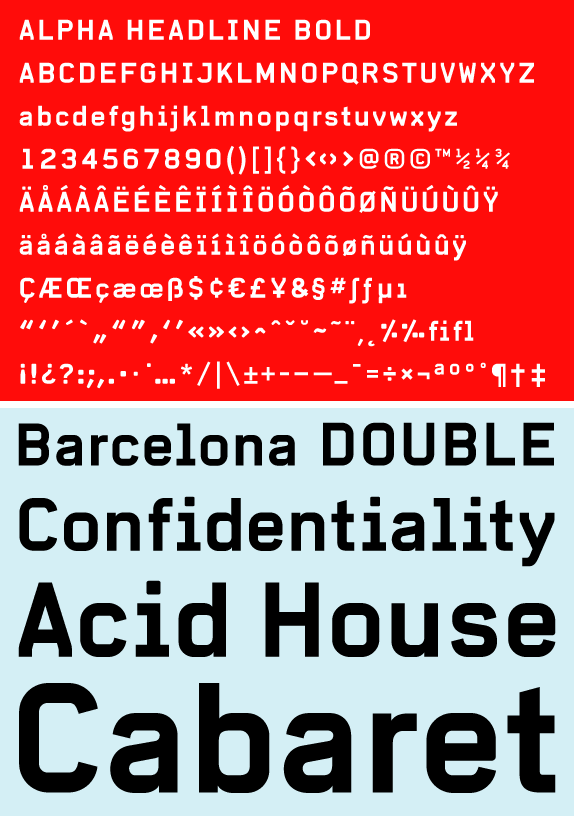
nein Simple, nein Magda, nein Typestar... ?
die alpha headline von lineto schaut sehr aehnlich aus,
ist dann in den details aber doch anders ...
Geht schon sehr in die Richtung. Jedoch sind die Arme des E bei meinem Beispiel alle gleich lang und die Serifen des I sind stärker ausgebildet.
Die Alpha kann man ja auch nicht käuflich erwerben - oder?
Also ein Nachbau???
Die Alpha kann man ja auch nicht käuflich erwerben - oder? Also ein Nachbau???
die alpha headline konnte man erwerben bevor sie
fuer mitsubishi ueberarbeitet wurde. damals allerdings
nur in versalien und einem schnitt ...